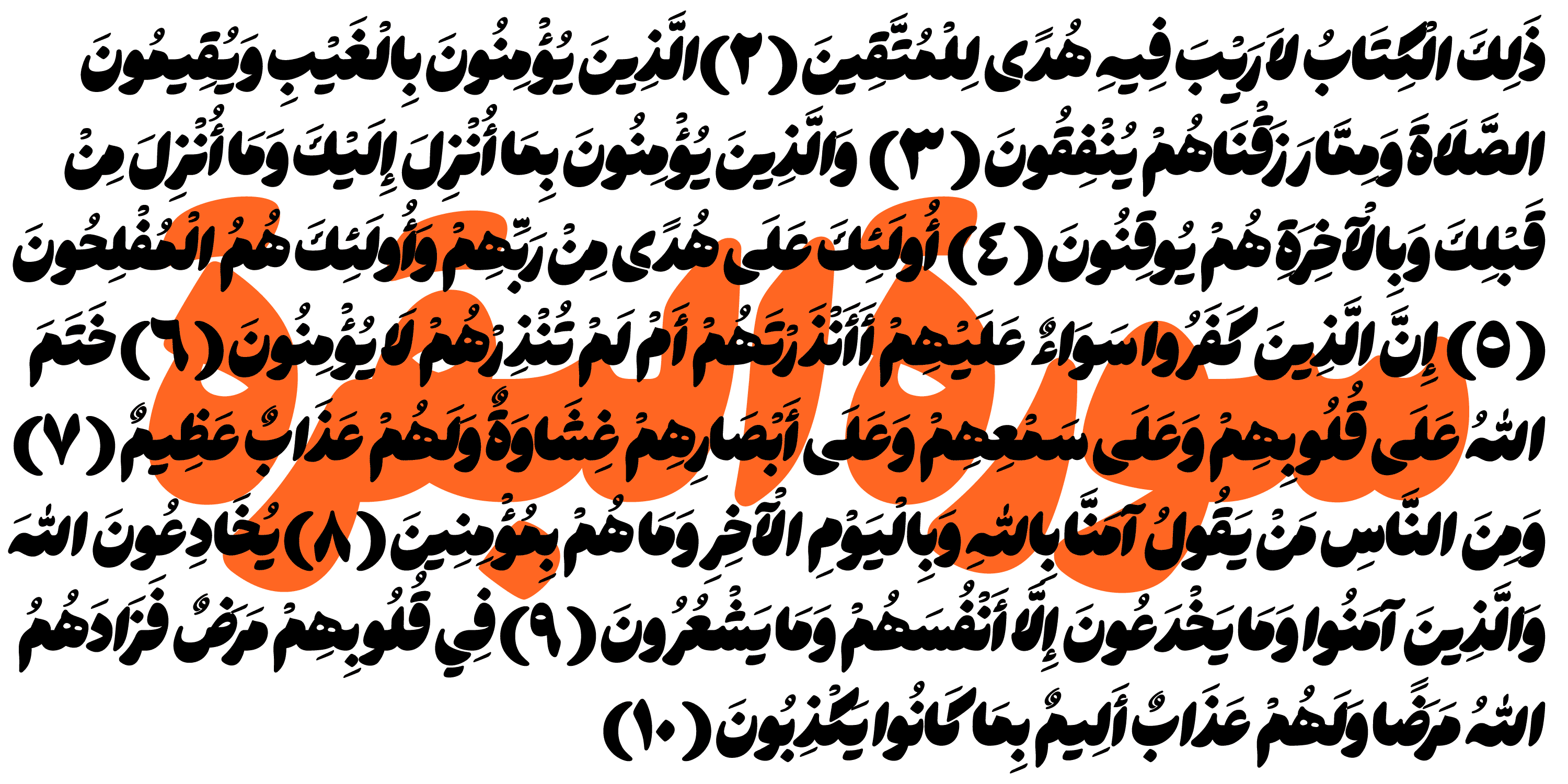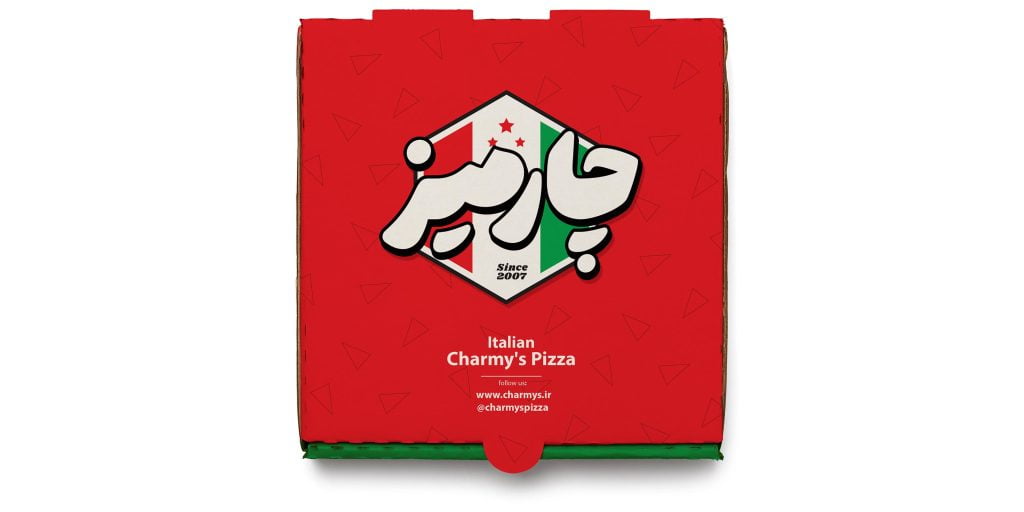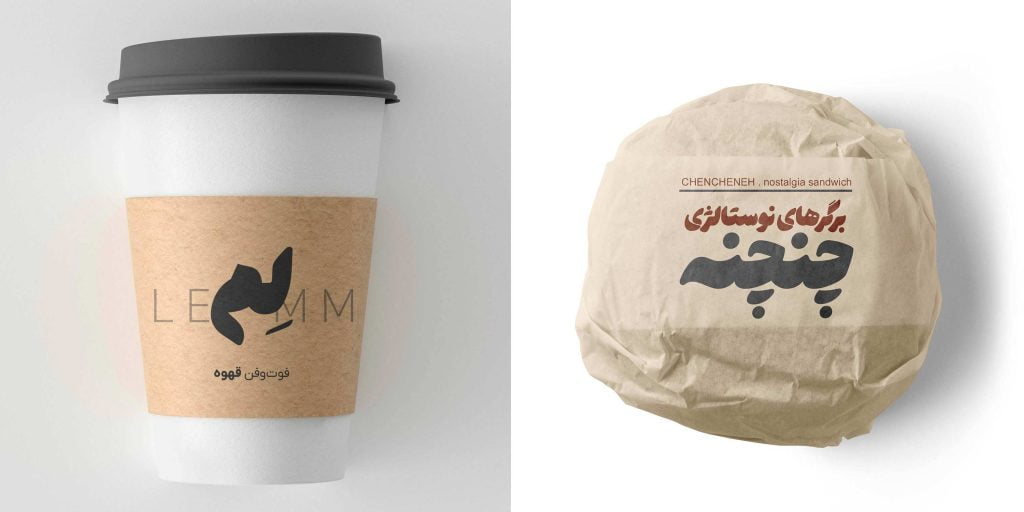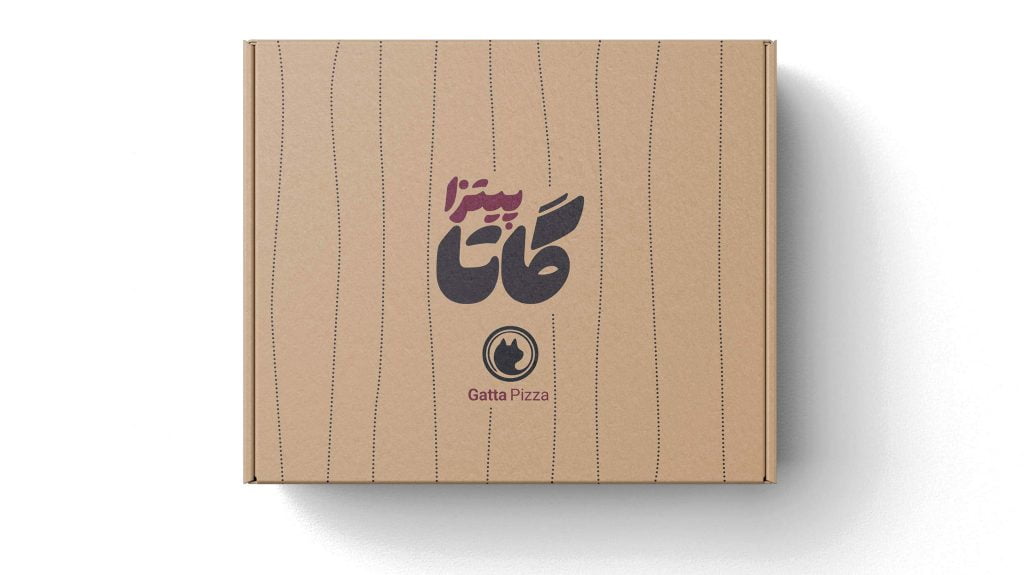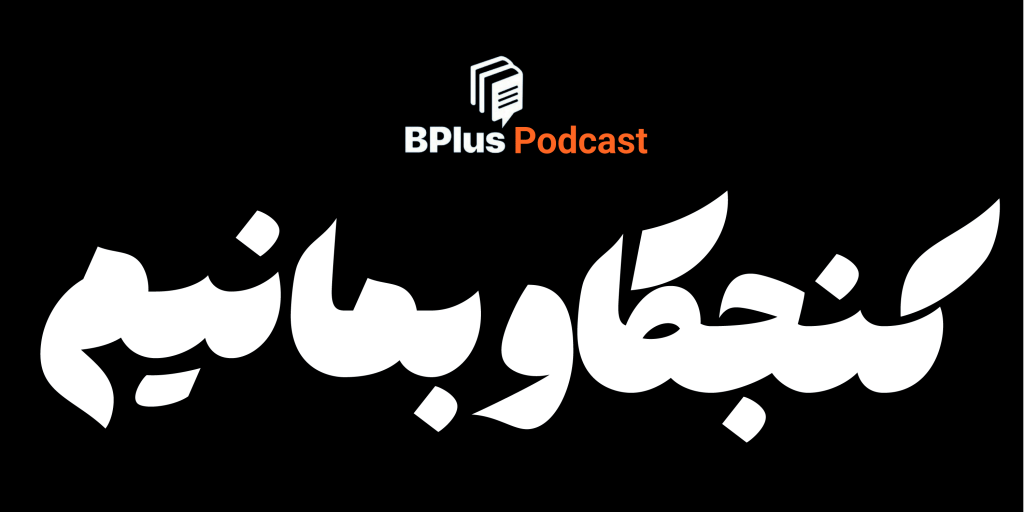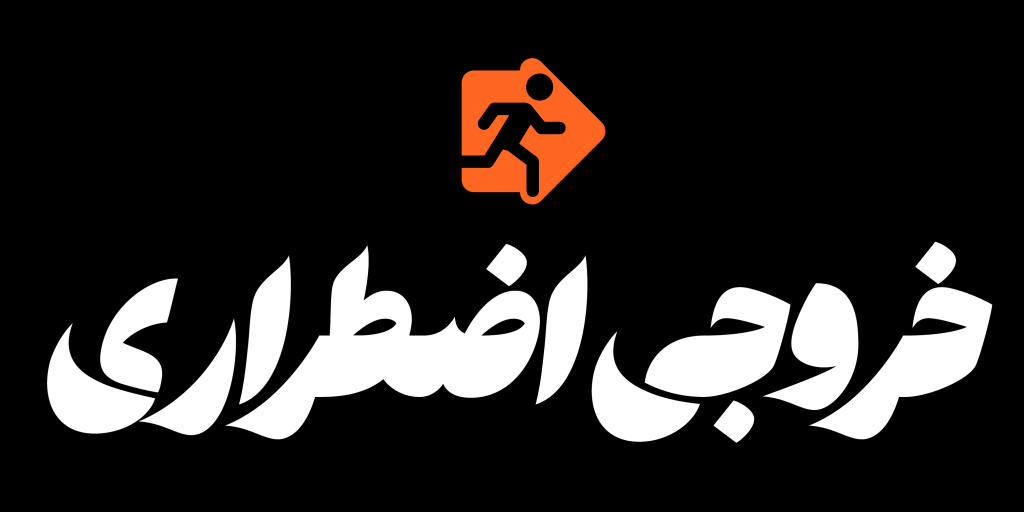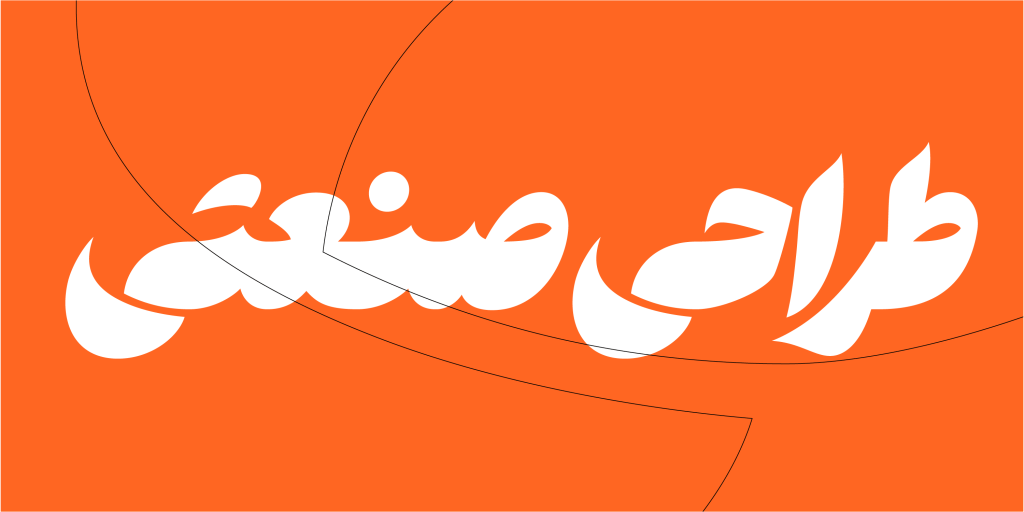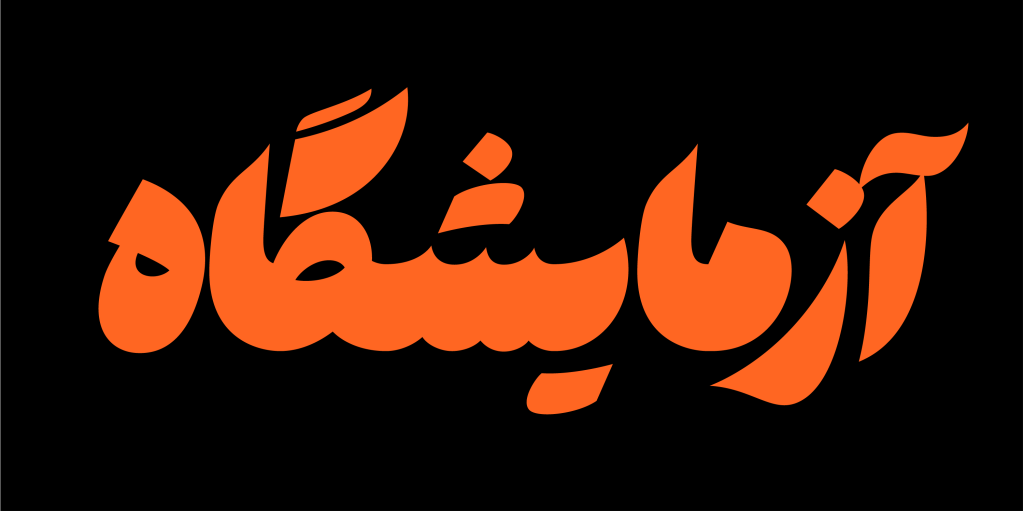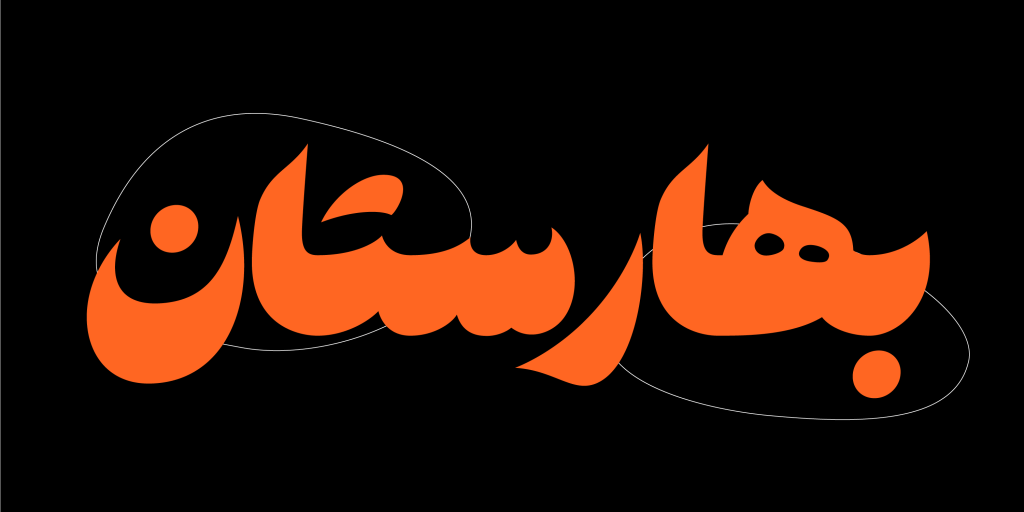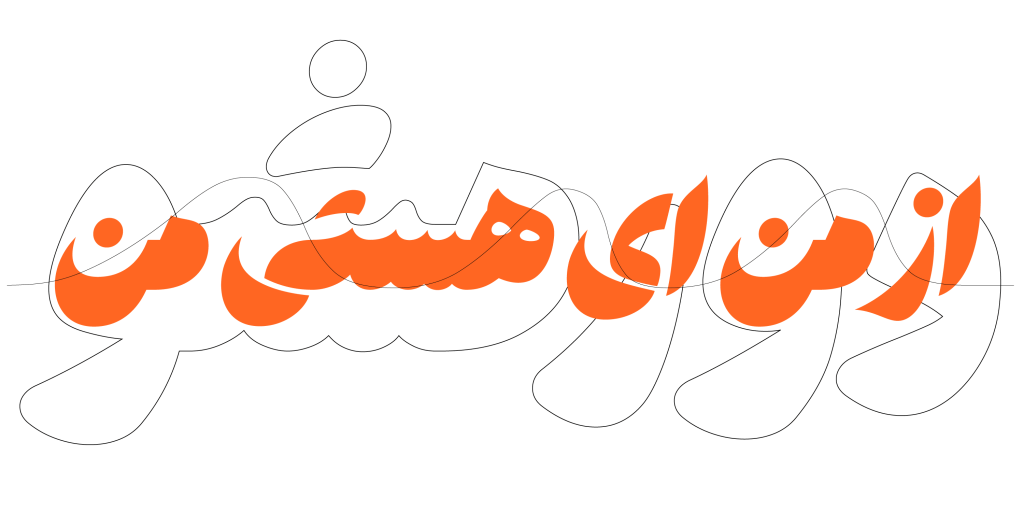
فونت هستی – آمیخته نسخ و نستعلیق
فونت هستی، آمیخته و ترکیب بندی شده از دو خانواده از خطوط زیبای خوشنویسی . یکی خط نستعلیق که بی شک کمتر کسی پیدا می شود که آن را نشناسد و این قلم هنوز برای ما دوست داشتنی و آشناست. هنوز هم شعر فارسی را جز با نستعلیق نمیتوانیم بپذیریم و اگر بخواهیم حس و حال فضای ایرانی را در نوشتهای نشان دهیم نستعلیق را انتخاب میکنیم.
آن دیگری خط نسخ که بر همگان آشناست . هستی تبلوری و آمیخته این دو خانواده است که از این حس آشنا و ترکیب دوست داشتنی یک تایپ فیس معاصر پدید آمده است. اگر به دنبال این سبک از قلم ها می باشید فونت پسته از نقطه نظر هم خانوادگی و سبک و شباهت بسیار نزدیک به هستی می باشد .
تمرکز بیشتر تایپ فیس هستی در طراحی حروف و عناوین و جنبه تبلیغاتی و بازاری این قلم می باشد . برای تیتر های درشت و بولد بوده و به نوعی جنبه نمایشی در درون خود دارد به عبارت ساده تر مناسب دیوار نویسیها و تبلیغات شهری که با قلمهای درشت خطاطی میشوند گزینه بسیار عالی می باشد، این قلم ظرافت های نستعلیق هنری را ندارد این حروف معمولاً برجسته تر و فشردهتر نوشته میشود.
در این تایپ فیس خبر و اثری از ترکیبات و اتصالات نستعلیق نیست اما شکل حروف تا حد امکان شبیه نستعلیق است.
برای فشردگی بیشتر، فرم حروف “ک ی ح” شکسته و منقطع شده است.
هستی و دریافت رتبه دوم رقابت جهانی 2024
نسخه جدید این قلم دارای دو سبک گرد Rounded و تیز Sharp است. هستی در سیزدهمین رقابت جهانی گرانشان (۲۰۲۴) در بخش فونتهای عربی جایزه دوم را کسب کرد. (داوران این دوره با سختگیری جایزه نخست را به هیچ اثری اهدا نکردند.)هرکدام از دو سبک گرد و تیز با دو سبک نقطه در بسته وجود دارد. (نقطه کلاسیک و نقطه گرد)
نسخه وریبل و به روز رسانی ها به زودی
هستی در حال به روز رسانی و آپدیت نسخه های بعدی خود می باشد . این به روز رسانی ها شامل نسخه وریبل ، ترکیبات در هستی و نزدیکی و شباهت بیشتر به این قلم را شامل خواهد شد . چرا که این تایپ فیس در نسخه اول خود، تا حد امکان ساده طراحی شده و فاقد ترکیبات است. دلیل سادگی این است که تمرکز بر دستیابی به شخصیت کلی تایپ باشد و پیش از هر توسعه تا حد امکان شکل حروف اصلاح شود. در مراحل بعد در قالب بهروز رسانی، امکانات کم کم به این قلم اضافه خواهد شد.